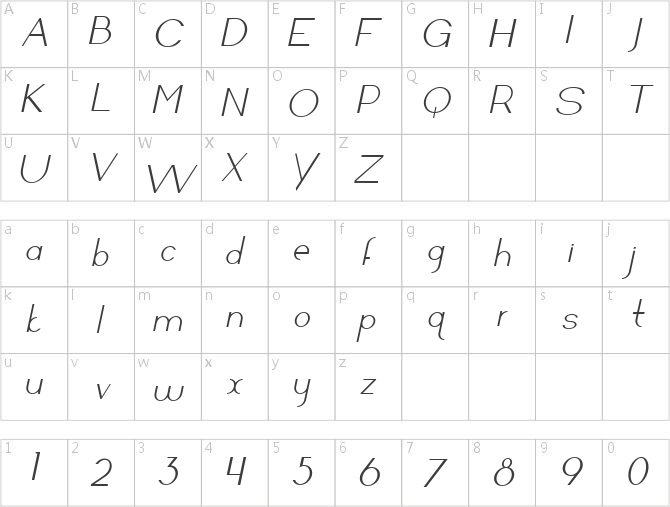
字体名称: arrival
arrivalsanddeparturesitalic
arrivalsanddeparturesitalic介绍
arrivalsanddeparturesitalic字体字库是一款让人赏心悦目、百看不厌的英文字体,适合各类广告和产品包装设计应用,字体大小0.06MB,格式为ttf字体,上传用户是rose,作者/版权方为未知